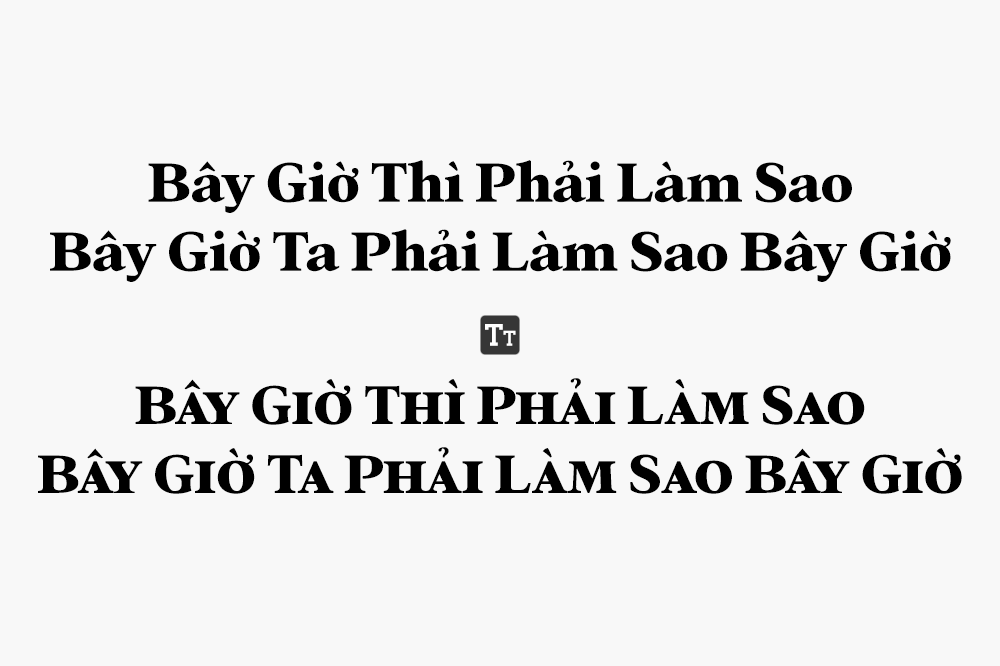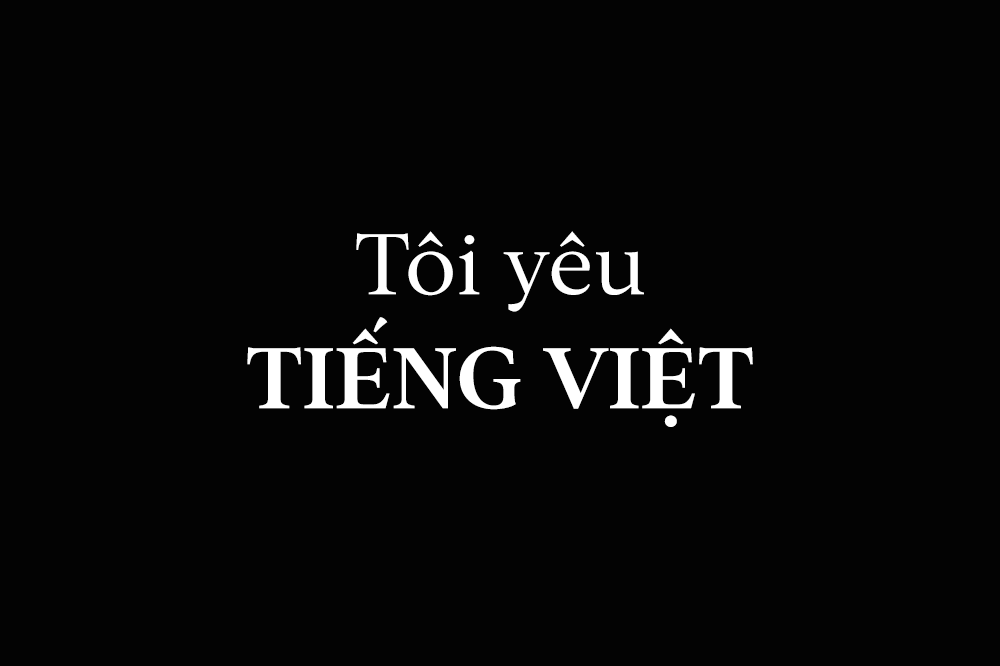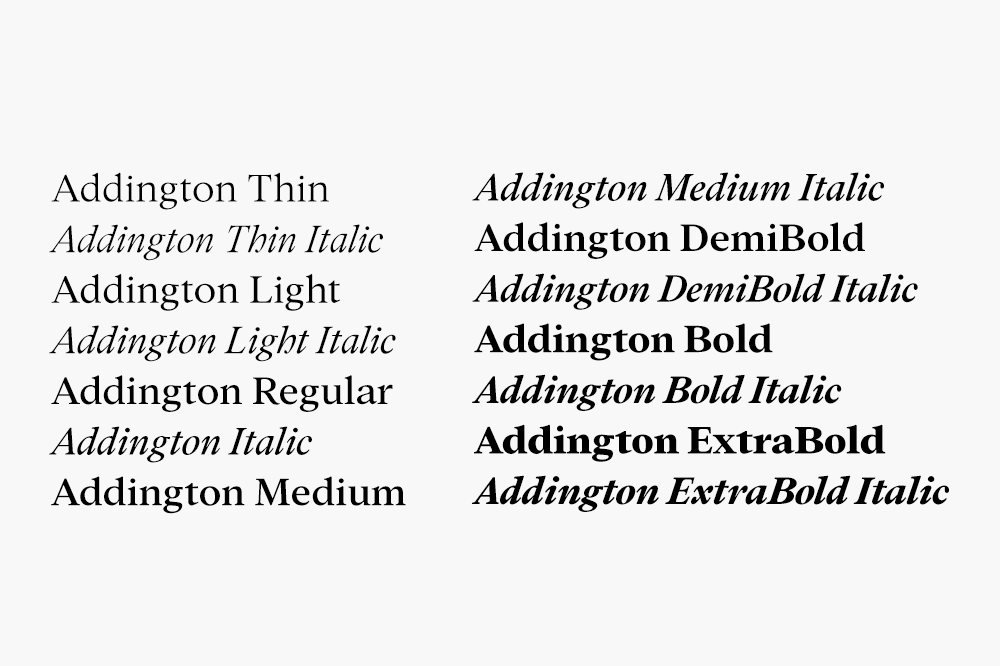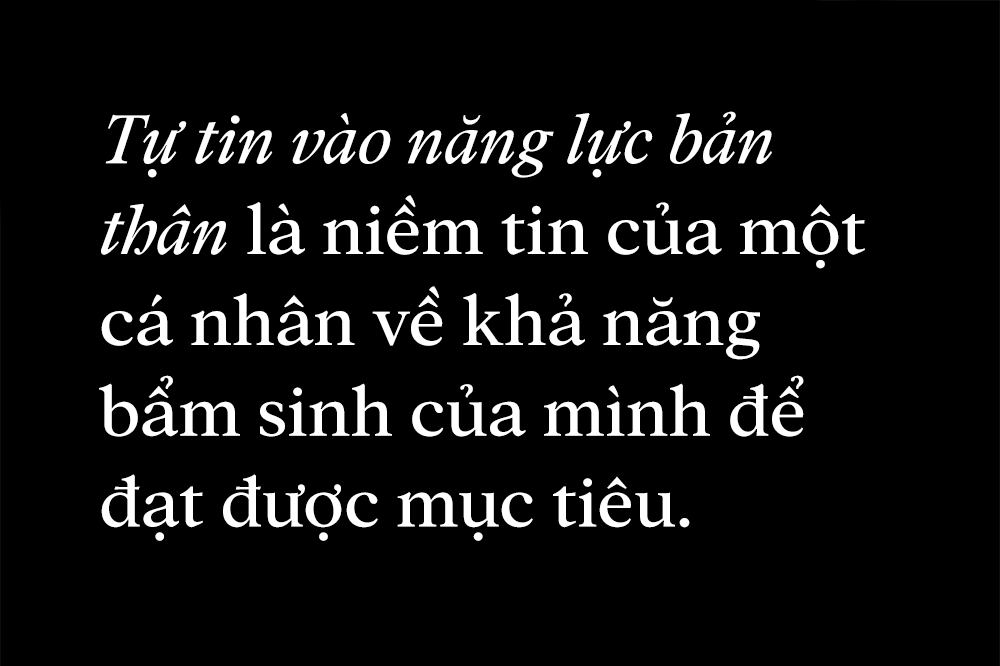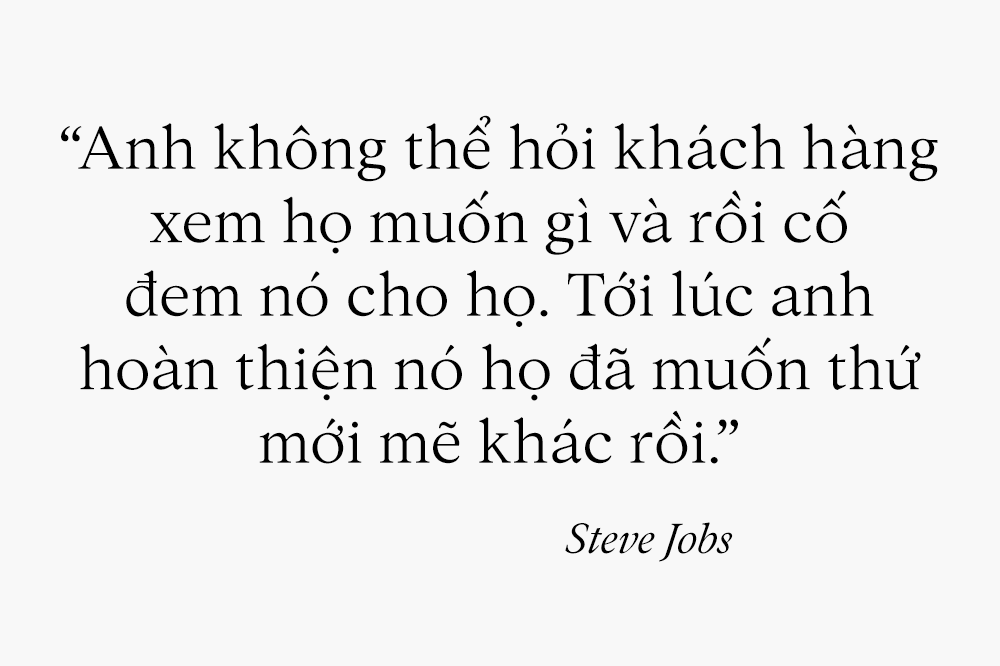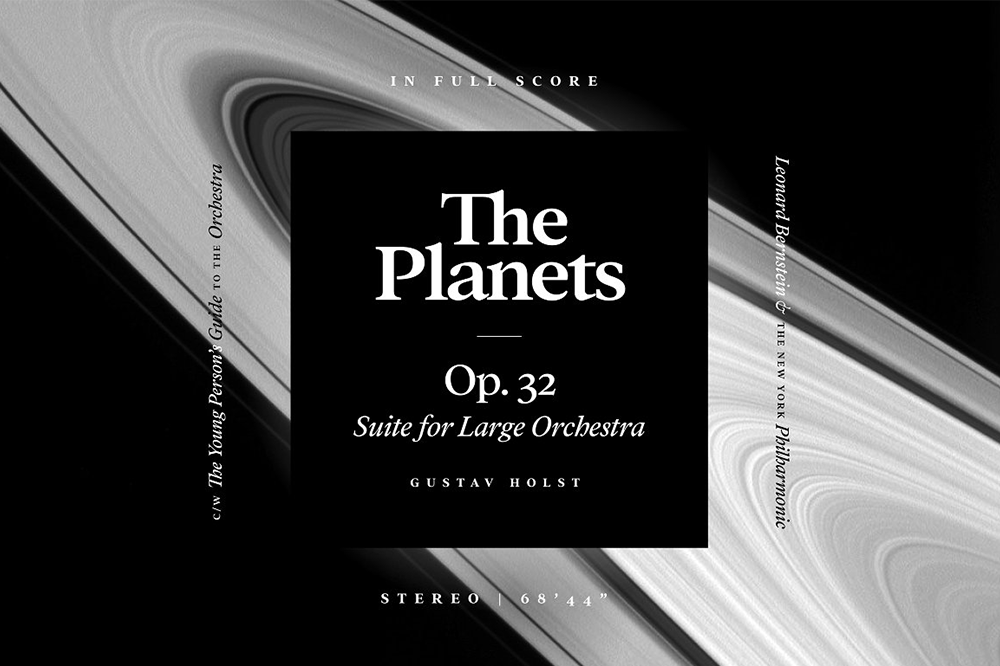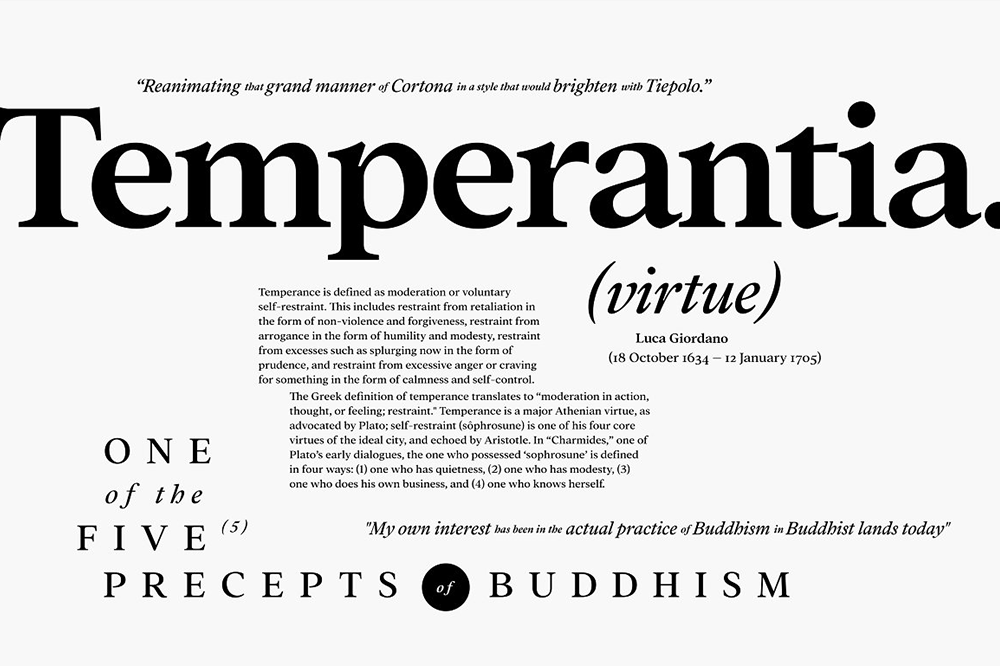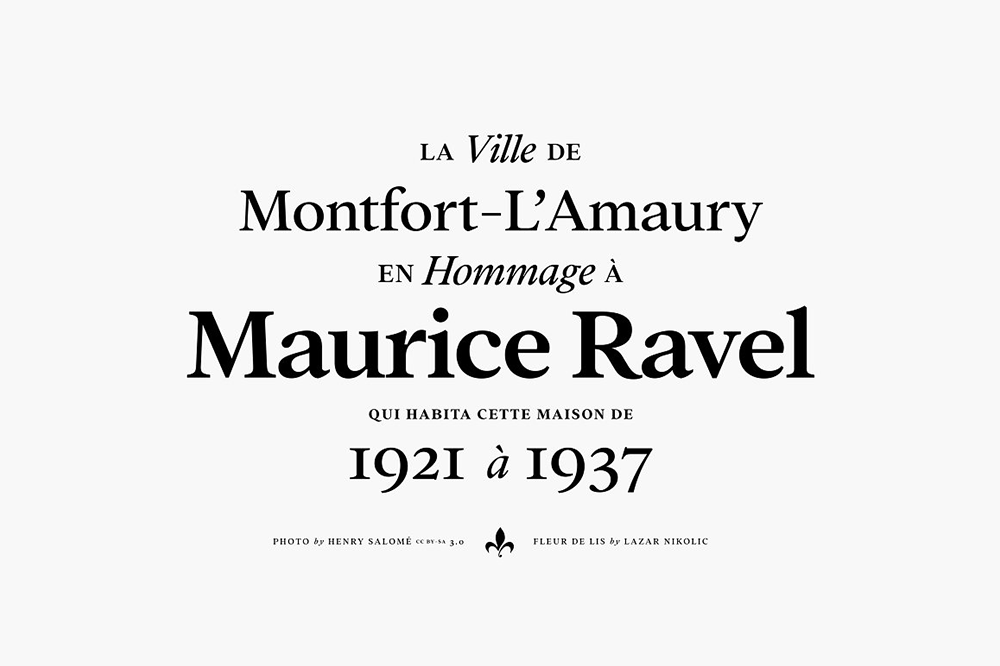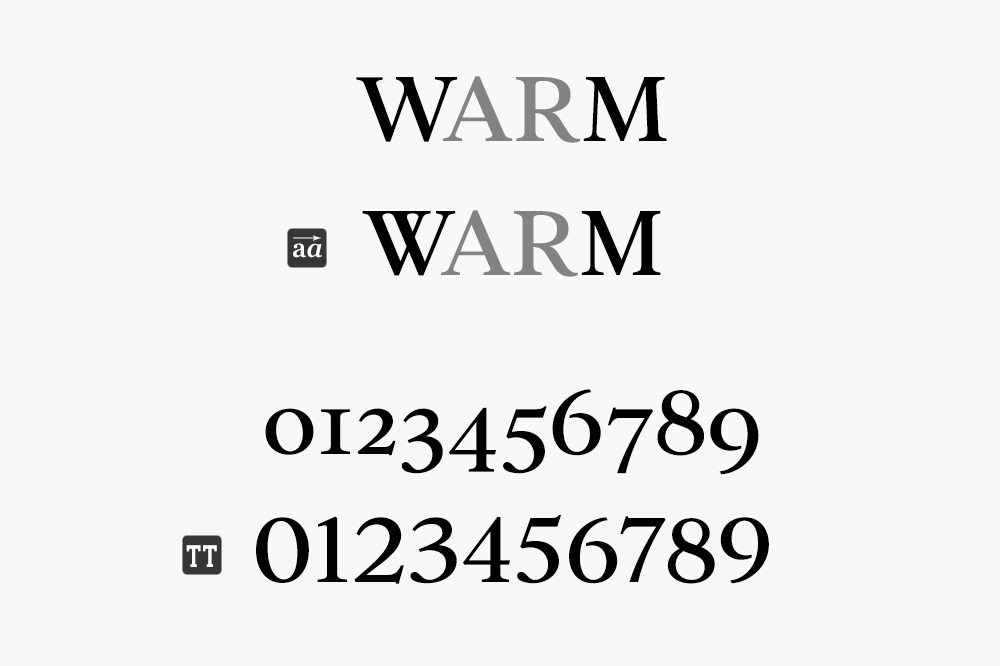
Addington là một phông chữ serif duyên dáng và đáng tin cậy, hữu ích trong mọi trường hợp. Đẹp nhưng cũng rất thực dụng, Addington được thiết kế để vượt trội trong các văn bản nặng chữ, đồng thời cũng là một kiểu chữ hiển thị mạnh mẽ và có năng lực. Bộ phông chữ này có bảy trọng lượng, chữ nghiêng thật và nhiều tính năng OpenType.
Nhà thiết kế: Connary Fagen
Nhà phát hành: Connary Fagen, Inc.